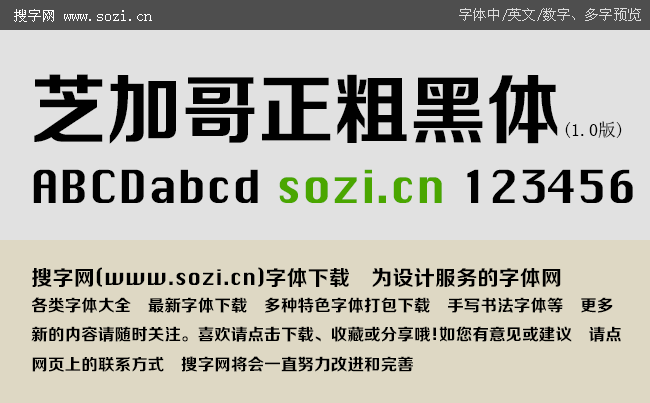
芝加哥正粗黑體
搜字網(wǎng)提供一款芝加哥正粗黑體中文藝術(shù)字體下載,芝加哥正粗黑體是一款中文藝術(shù)黑體字體,該字體端莊大方、品質(zhì)精良,整體效果非常出色。可以應(yīng)用于廣告設(shè)計(jì)、平面設(shè)計(jì)、產(chǎn)品包裝、報(bào)刊雜志等領(lǐng)域。